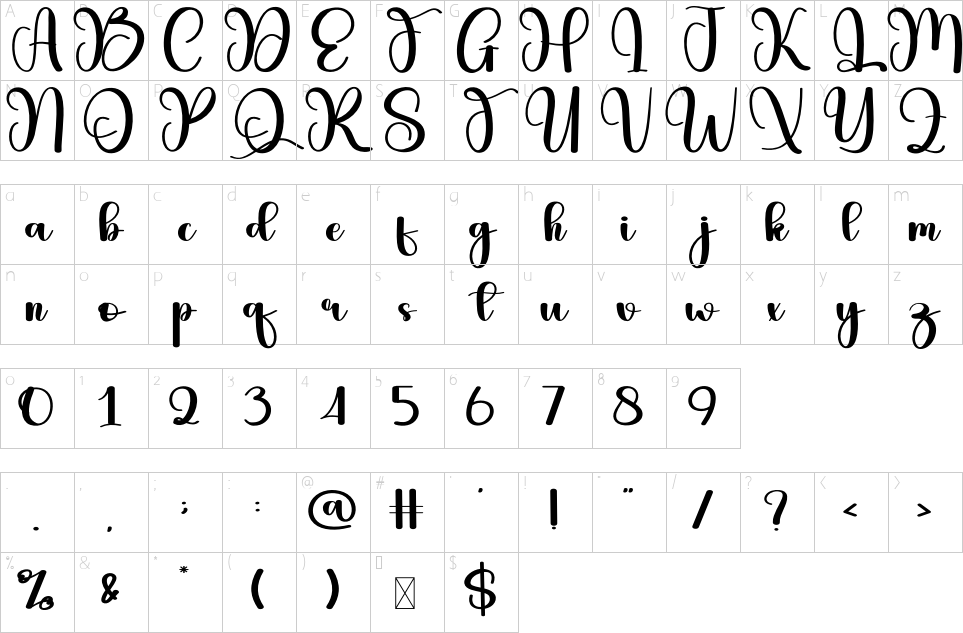
Pinky Font | 1001 Free Fonts – Fonte Grátis
A Pinky font é uma opção elegante para designers e criadores de conteúdo que buscam personalidade em suas criações digitais. Ela foi projetada por William Jhordy e, embora não tenhamos informações adicionais sobre seu design, a fonte tem um visual único e desafiador que certamente adicionará um toque especial a seu trabalho. Com a Pinky font, os designers podem experimentar uma novidade em seu portfólio. Desde o uso em artigos de texto até o design de logotipos, esta font livre de charge é versátil e pronta para encaixar em uma variedade de ambientes. Se você está procurando por uma fonte que vai além da básica, a Pinky font pode ser a escolha perfeita. Com seu download fácil de Windows e Mac, ela oferece uma maneira prática de incorporar esse charme único em projetos digitais.